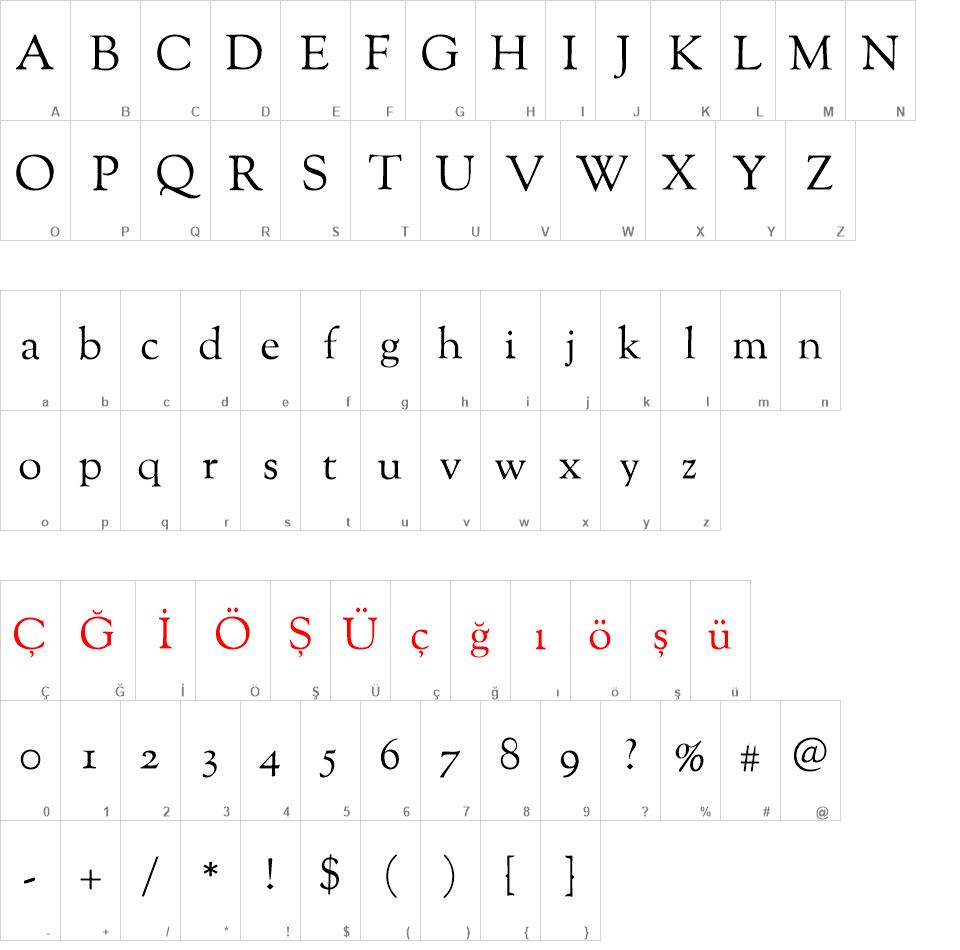
OFL Sorts Mill Goudy Font Family
Die Wiederbelebung von Frederic Goudys "Goudy Oldstyle" mit regulären und kursiven Stilen und einem erweiterten lateinischen Charakter.